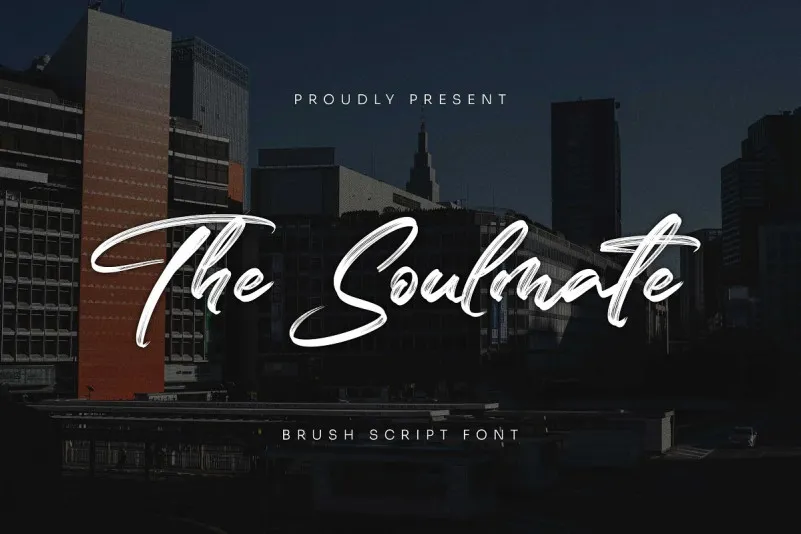
The Soulmate Font – Download Grátis
Esta é uma fonte brush com letras afiadas e belas que criam um estilo moderno, trendy e elegante. As letras são feitas com esponjas no papel. Então são rascunhadas novamente cuidadosamente num formato vectorial. É por isso que a Soulmate tem características encantadoras, autênticas e descontraídas. Ela transmite um naturalismo mais profundo em seu texto. Você pode ativar o Painel Ligatura OpenType para que a Soulmate seja perfeita para projetos de design, identidade visual, criação de logotipo e embalagens de produto. A fonte tem uma aparência realista que proporciona um ar natural e único ao seu texto. Seja você criando um logotipo icônico ou trabalhando em uma coleção de pacotes de produtos, a Soulmate trará vida e um toque pessoal para seus designs. Esta é uma fonte excelente para criar um ambiente autêntico e contemporâneo, perfeita para quem busca uma identidade visual forte e única.